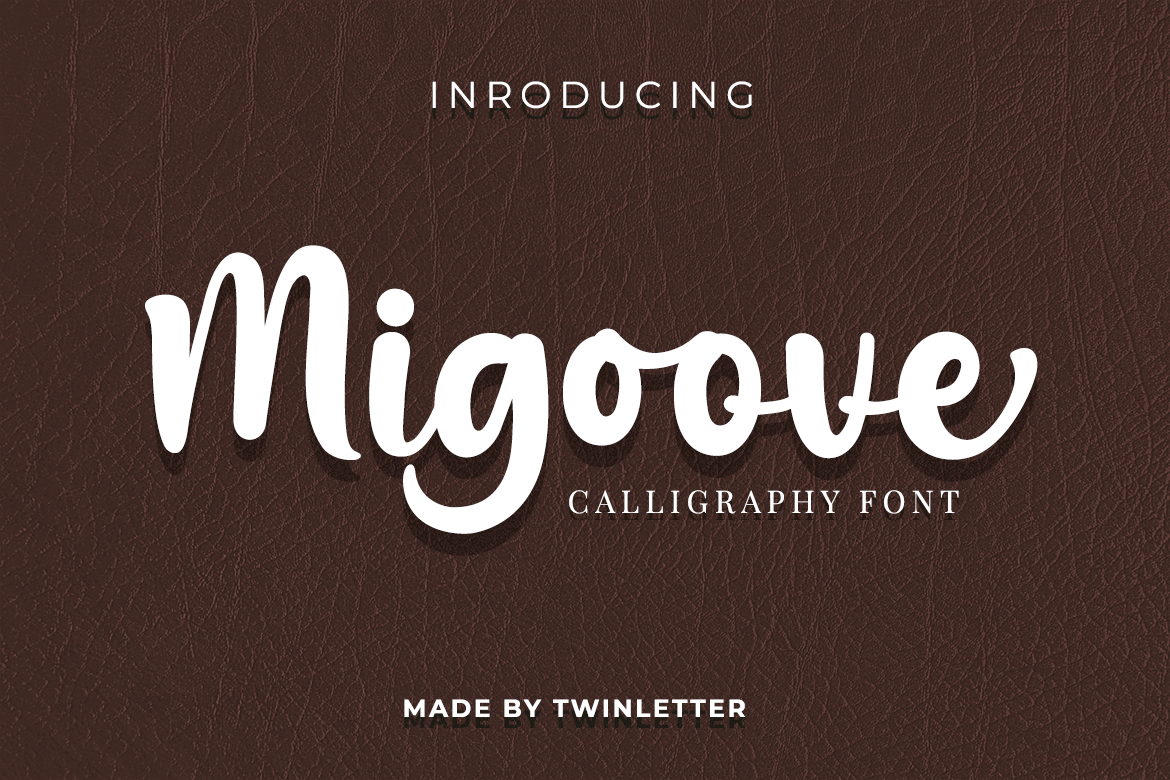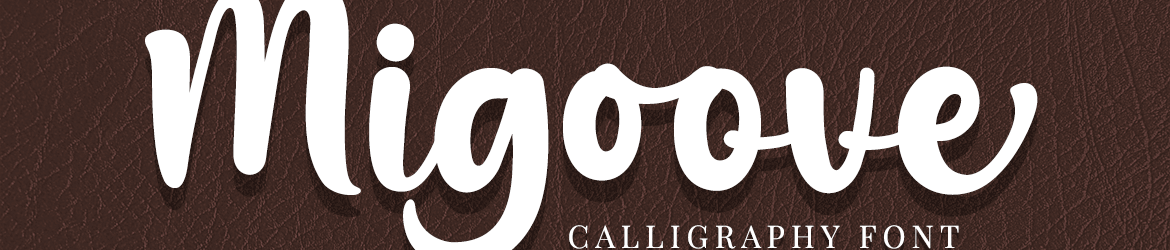
Migoove Font – Download Grátis
Esta é uma fonte script que possui características atraentes e forte em cada letra. Perfeita para quem busca estilizar seus projetos no trabalho ou na vida pessoal, pois ela torna a experiência de criar um design mais divertida e gratificante. Com diversas opções disponíveis, essa fonte permite flexibilidade ao criador, facilitando a criação de um blend personalizado que atenda às suas necessidades criativas específicas. O Migoove Font é uma escolha inteligente para quem busca agregar sofisticação e estilo em seus trabalhos. Aqui está um tipo interessante para complementar sua coleção de fontes.